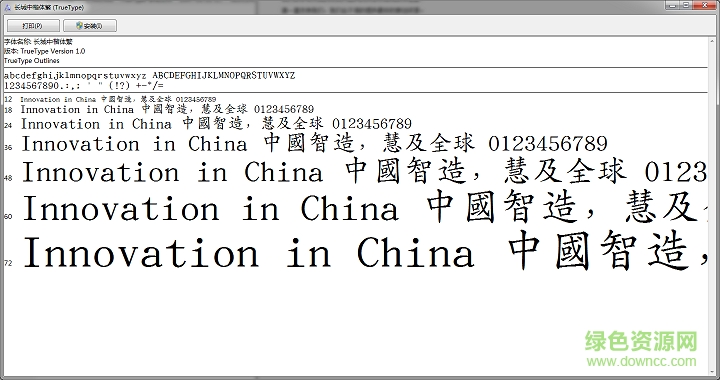
tzenkai medium字體(長(zhǎng)城中楷體繁)是一款筆畫(huà)平直結(jié)構(gòu)工整的長(zhǎng)城楷書(shū)字體,該字體清秀生動(dòng),點(diǎn)畫(huà)清楚,疏密得當(dāng),十分美觀,喜歡的朋友快來(lái)綠色資源網(wǎng)下載收藏吧!